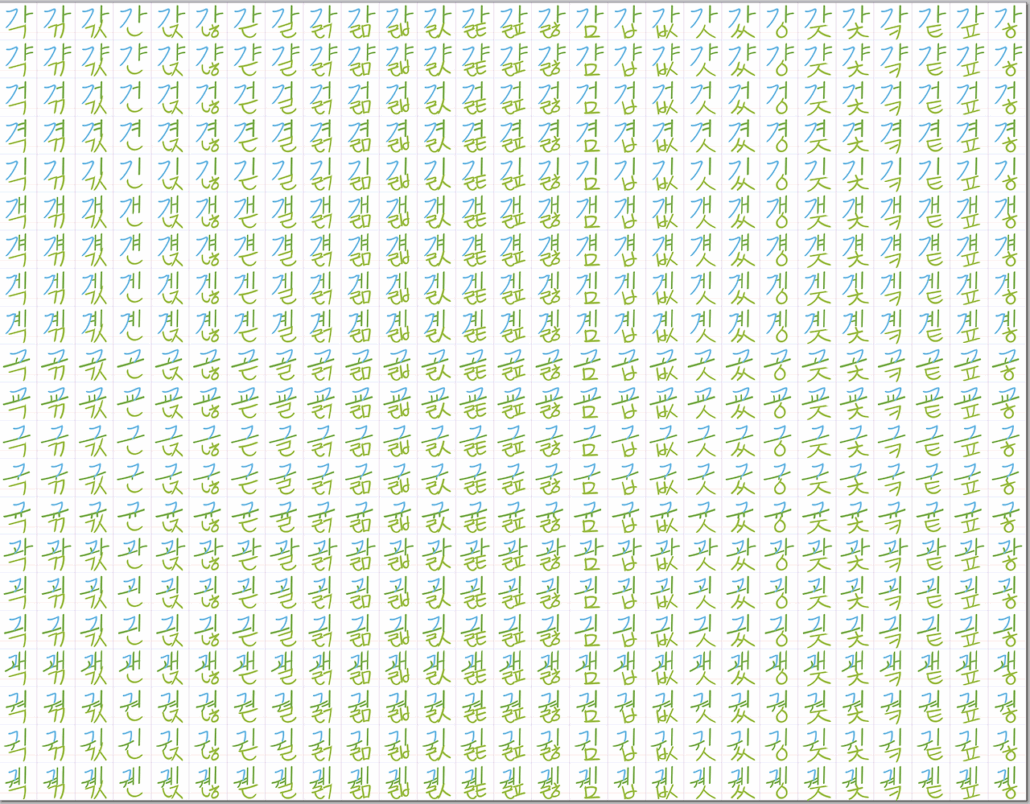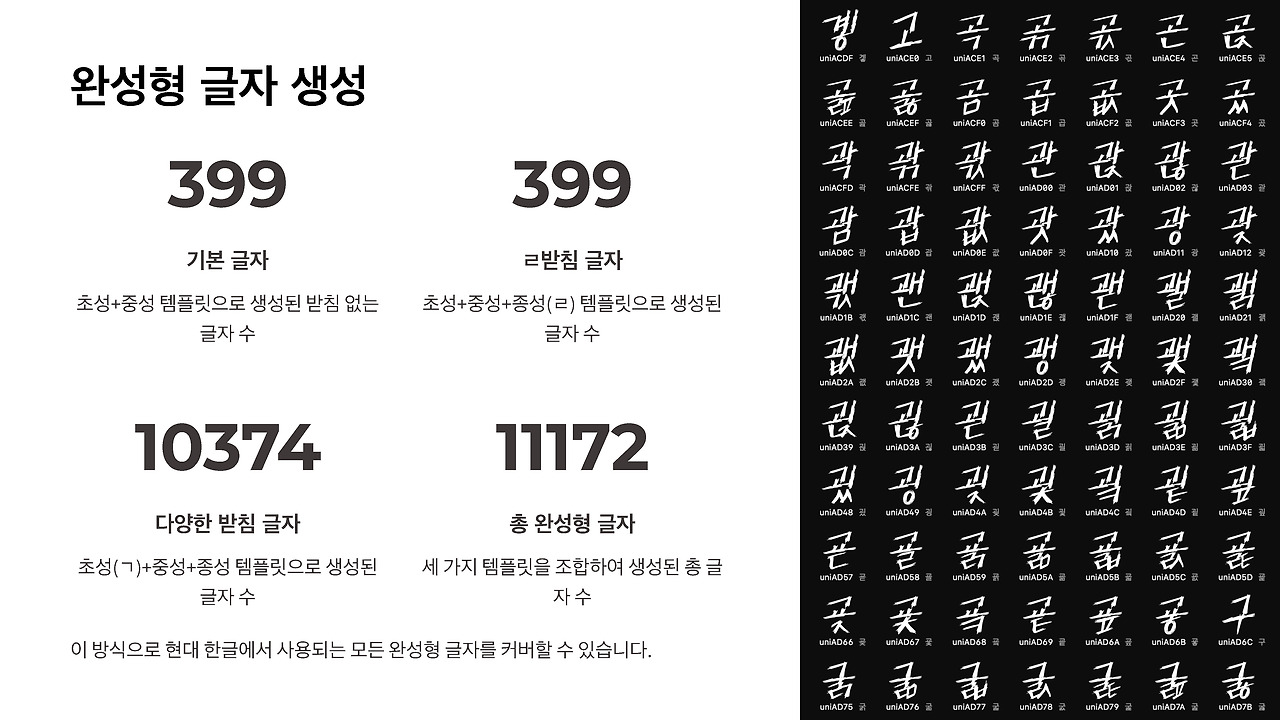
손글씨 A9Box (A9박스) 베타 폰트 0.1
A9Box (A9박스) 폰트 0.1
한글만 있는 폰트입니다. 손글씨 폰트로 봄봄스쿨에서 제작했습니다.
베타 폰트이며 한글만 있습니다. 현재 11,172자를 기본으로 만들었으며 게시판에 추가 수정이 있으면 버전을 자료실에 판올림 버전을 추가해서 계속 올릴 예정입니다.